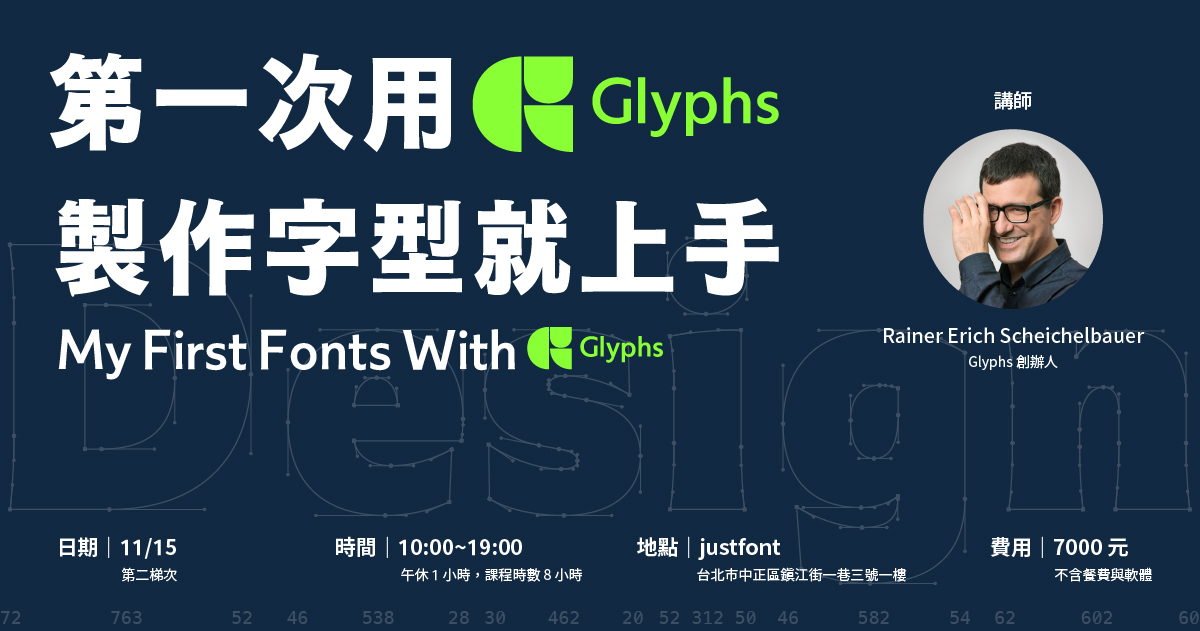
第一次用 Glyphs 製作字型就上手 My First Fonts with Glyphs
全球獨立字體設計師愛用的專業字型設計軟體 Glyphs 創辦人 Rainer Erich Scheichelbauer 首度來台!
在一天的工作坊之內,完成兩種風格的拉丁字母字型創作!
Glyphs 作為字型設計專用軟體,有許多更加細緻的功能,幫助設計師雕琢設計細節。
本次工作坊,將由 Glyphs 創辦人 Rainer Erich Scheichelbauer
親自教授 Glyphs 操作方式,並在工作坊期間內完成手寫字體和無襯線體,兩種不同風格的字型作品!
Rainer Erich Scheichelbauer, founder of Glyphs—the professional type design software favoured by independent type designers—will visit Taiwan for the first time!
In this one-day workshop, participants will complete two Latin typefaces from scratch.
As a dedicated tool for type design, Glyphs offers a range of refined functions that help designers perfect every detail of their work.
In this workshop, Glyphs founder Rainer Erich Scheichelbauer will personally teach how to use the software and guide participants through the process of creating two typefaces in distinct styles within a day.
課程內容 Contents
手寫字體
把你的手寫作品變成一套字型!學習筆畫、組件與筆帽組件,增添不同造型的替換字符,並透過 OpenType 功能讓你的字型看起來更自然、更有手寫感。
Handwriting Font
Turn your handwriting into a font, work with strokes, composites and caps, add alternates and an OpenType feature to make your font look more authentic.
幾何無襯線字體
從零開始打造一款自己的拉丁字體。學習貝茲曲線、系統化字距設定與組件設計,並建立粗細軸(weight axis),將字體從 Light 到 Extrabold 自動生成完整的字族。
Geometric Sans
Build your own Latin font, learn béziers, systematic spacing, composites, add a weight axis and interpolate a font family from Light to Extrabold.
關於講師
Rainer Erich(Eric)Scheichelbauer 出生於維也納,先後修讀攝影、哲學與荷蘭語。現職為字體設計師,教授字體設計、開辦相關工作坊,並將與排印學相關的荷蘭語書籍譯成德文,同時撰寫文章與 Python 腳本。Rainer 自 2012 年加入 Glyphs 團隊以來,一直負責撰寫教學與使用手冊。於維也納,他經營名為「Schriftlabor」的小型字型工作室與字型工程服務。
Rainer Erich (Eric) Scheichelbauer was born in Vienna, and studied photography, philosophy and Dutch. Today, he creates and produces typefaces, teaches type design, gives type design workshops, translates Dutch books on typography into German, and writes articles and Python scripts. Rainer joined the Glyphs team in 2012, and has been writing tutorials and the handbook. In Vienna, he runs a small foundry and font engineering service called “Schriftlabor“.
關於 Glyphs